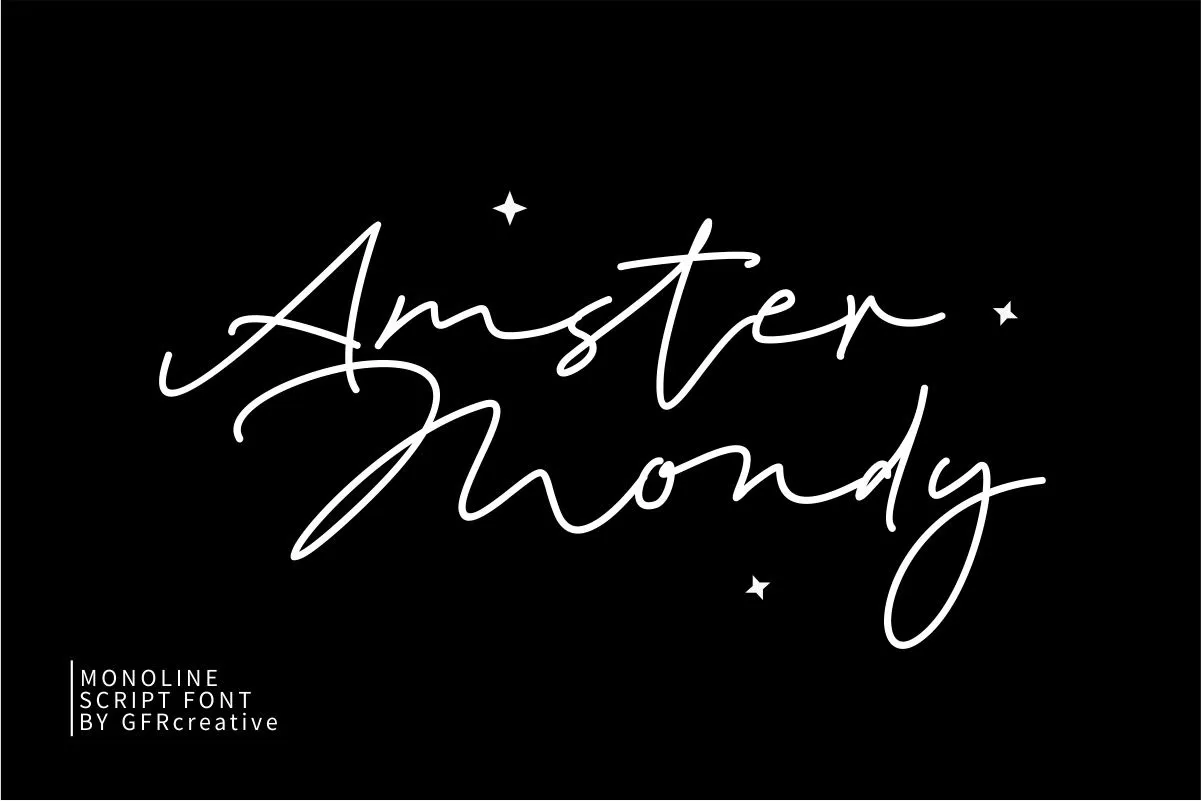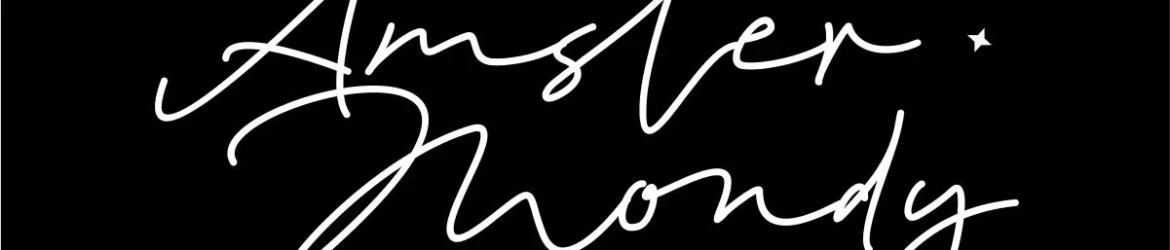
Amster Mondy Handwritten Font – Download Grátis
Esta é uma fonte tipo escrita à mão com traços delicados e doces, onde as letras dançam ao longo do nível base. Ideal para aplicar em diversos projetos digitais ou impressos, sua elegância a tornará perfeitamente adaptável tanto para design gráfico quanto para criações visuais mais pessoais. Seja para textos de texto ou para criar efeitos interessantes, esta fonte oferece um toque delicado que certamente enriquecerá seus designs. Aproveite-a no próximo projeto criativo e explore a delicadeza desta fonte, onde cada traço parece fluir naturalmente de uma mão à outra.